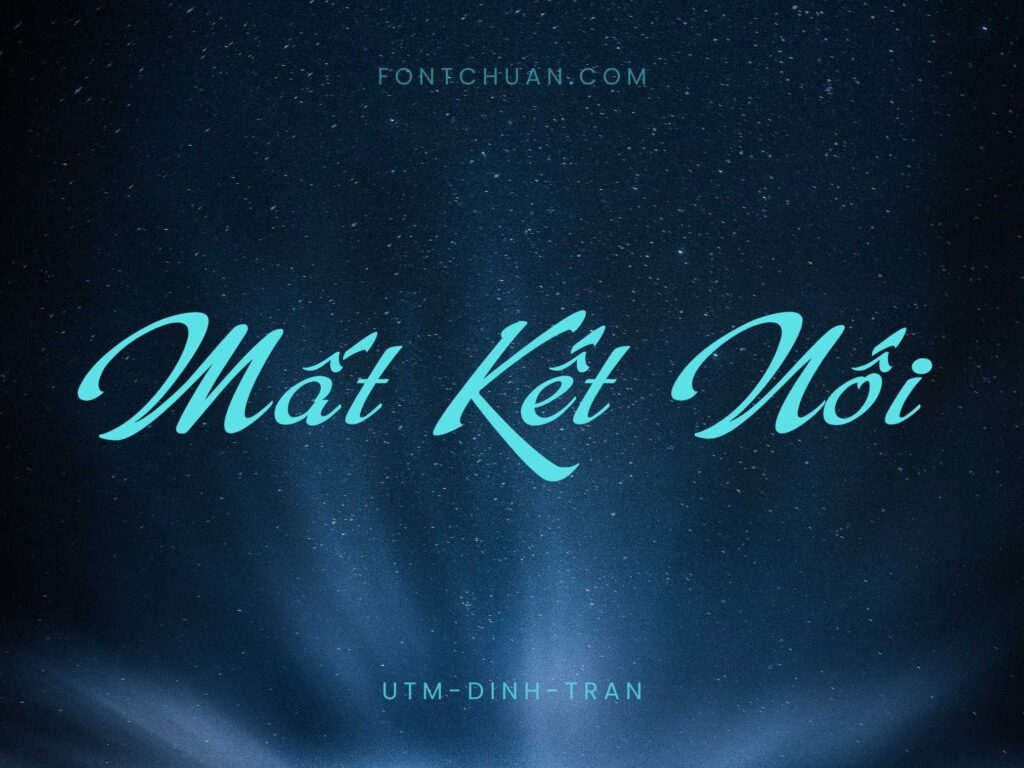
Font UTM Dinh Tran Việt Hóa là một kiểu Font chữ cổ trang, gợi nhớ đến những nét chữ truyền thống của Việt Nam. Với các đường nét uốn lượn mềm mại nhưng vẫn giữ được sự mạnh mẽ, font này phù hợp cho các thiết kế mang tính lịch sử, văn hóa và truyền thống.
Font này đã được Việt hóa để hỗ trợ đầy đủ tiếng Việt bởi Thiên Minh, ngoài ra còn hỗ trợ hơn 200 ngôn ngữ khác. Thành viên của Font Chuẩn đã sưu tầm và chọn lọc font này nhằm đáp ứng nhu cầu của người dùng trong thiết kế và ứng dụng thực tế. Font có đặc điểm nổi bật với đường nét thanh thoát, phù hợp với các dự án như thiết kế poster, ấn phẩm văn hóa, bìa sách, và nhiều lĩnh vực khác.